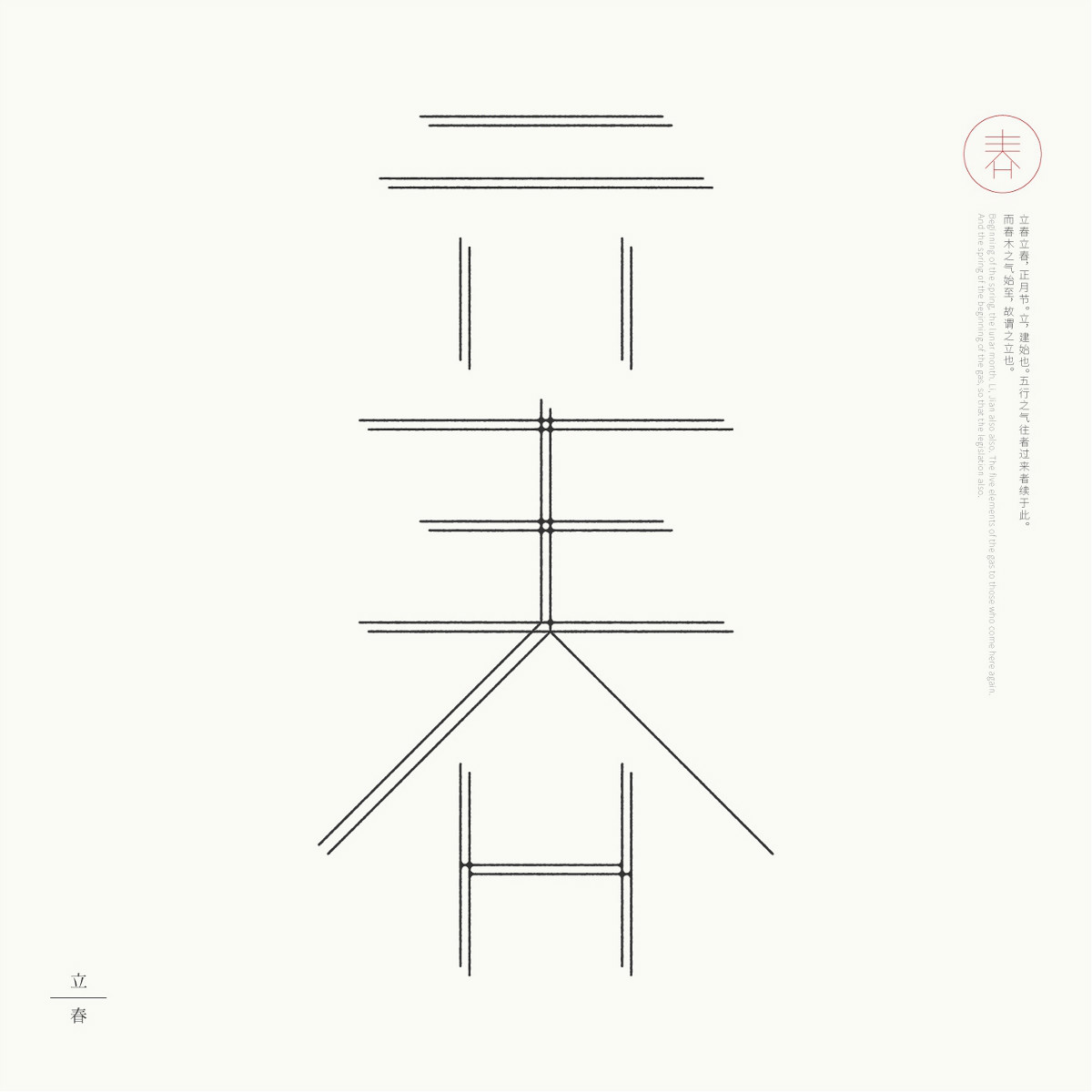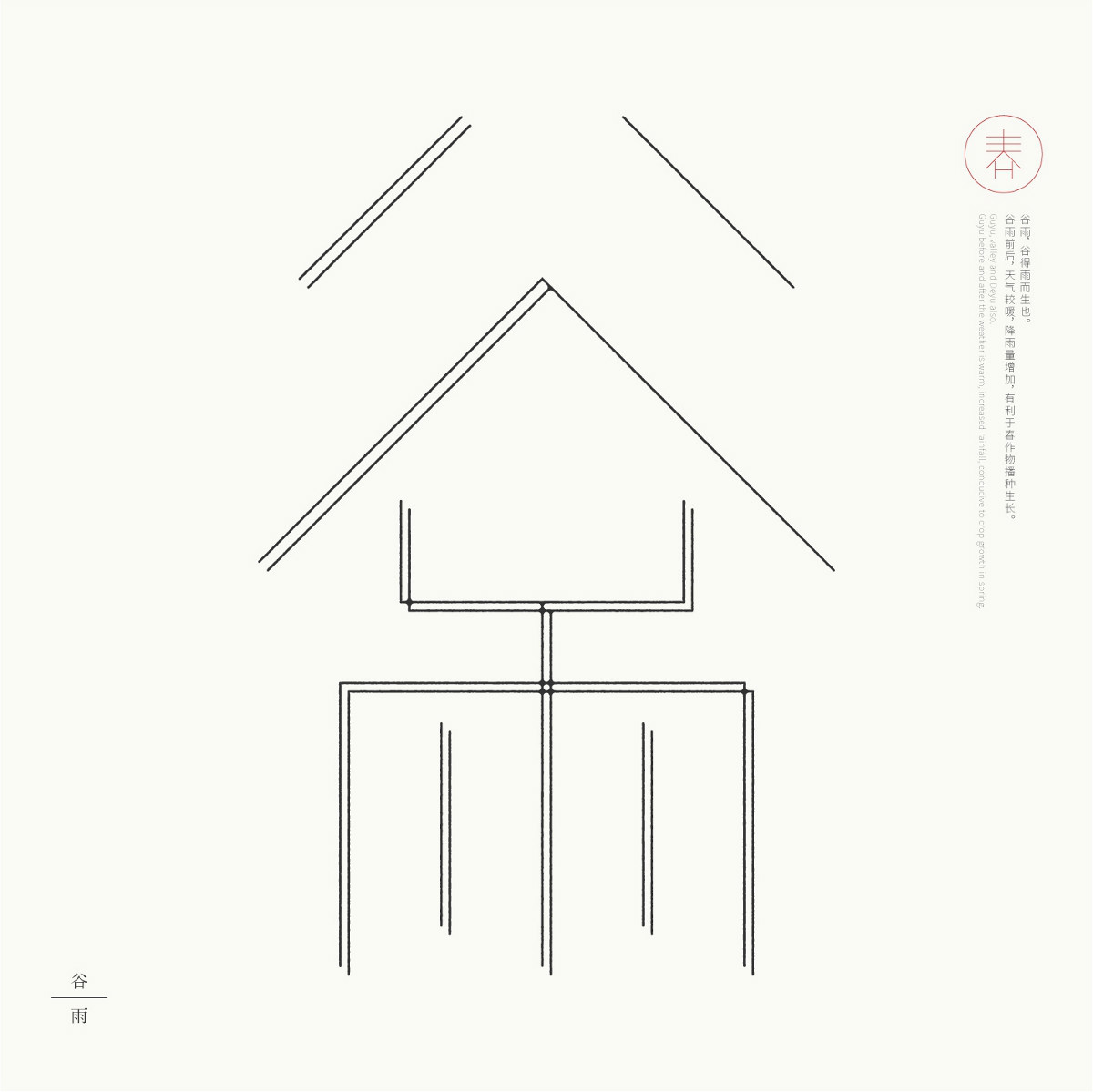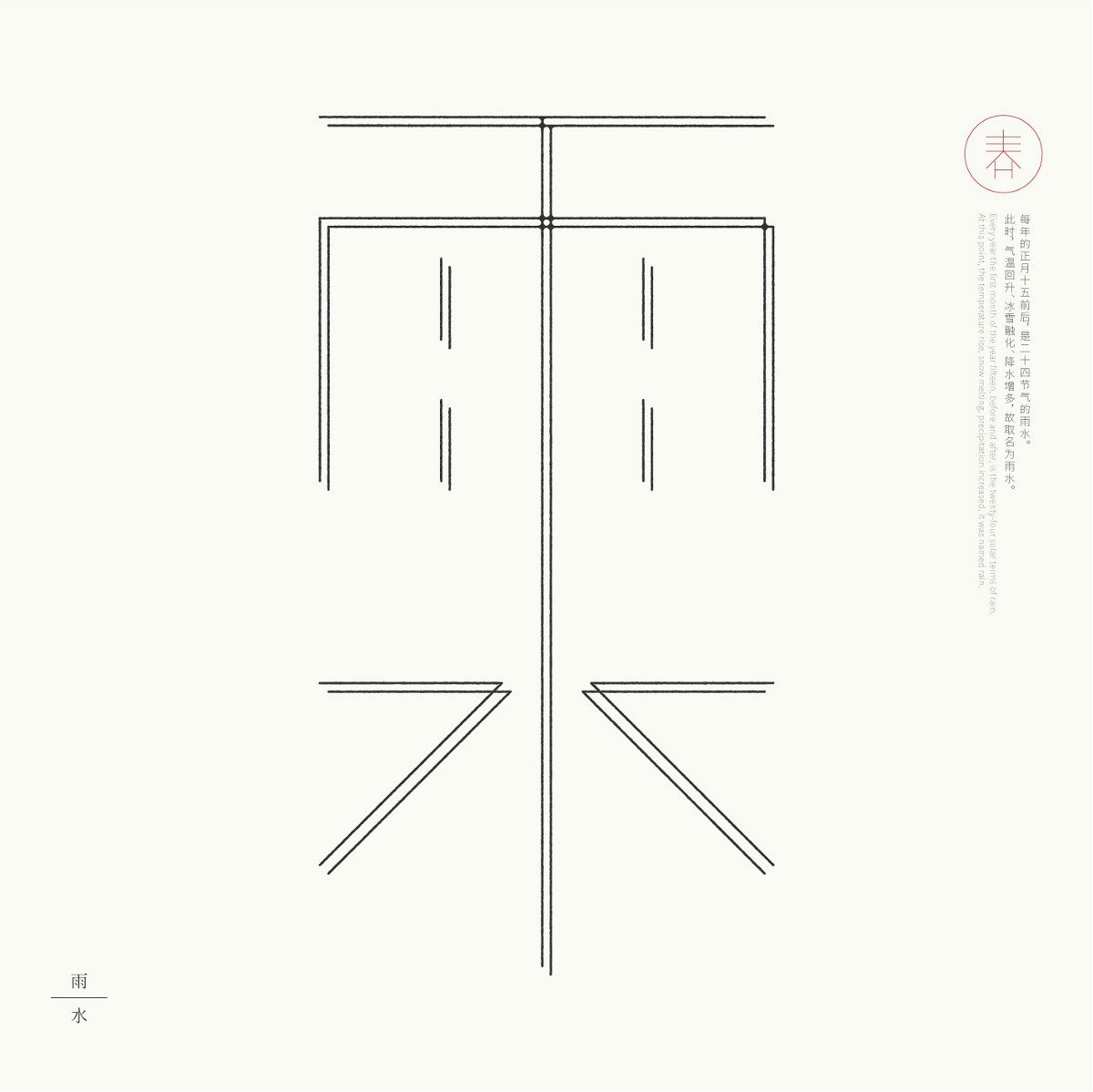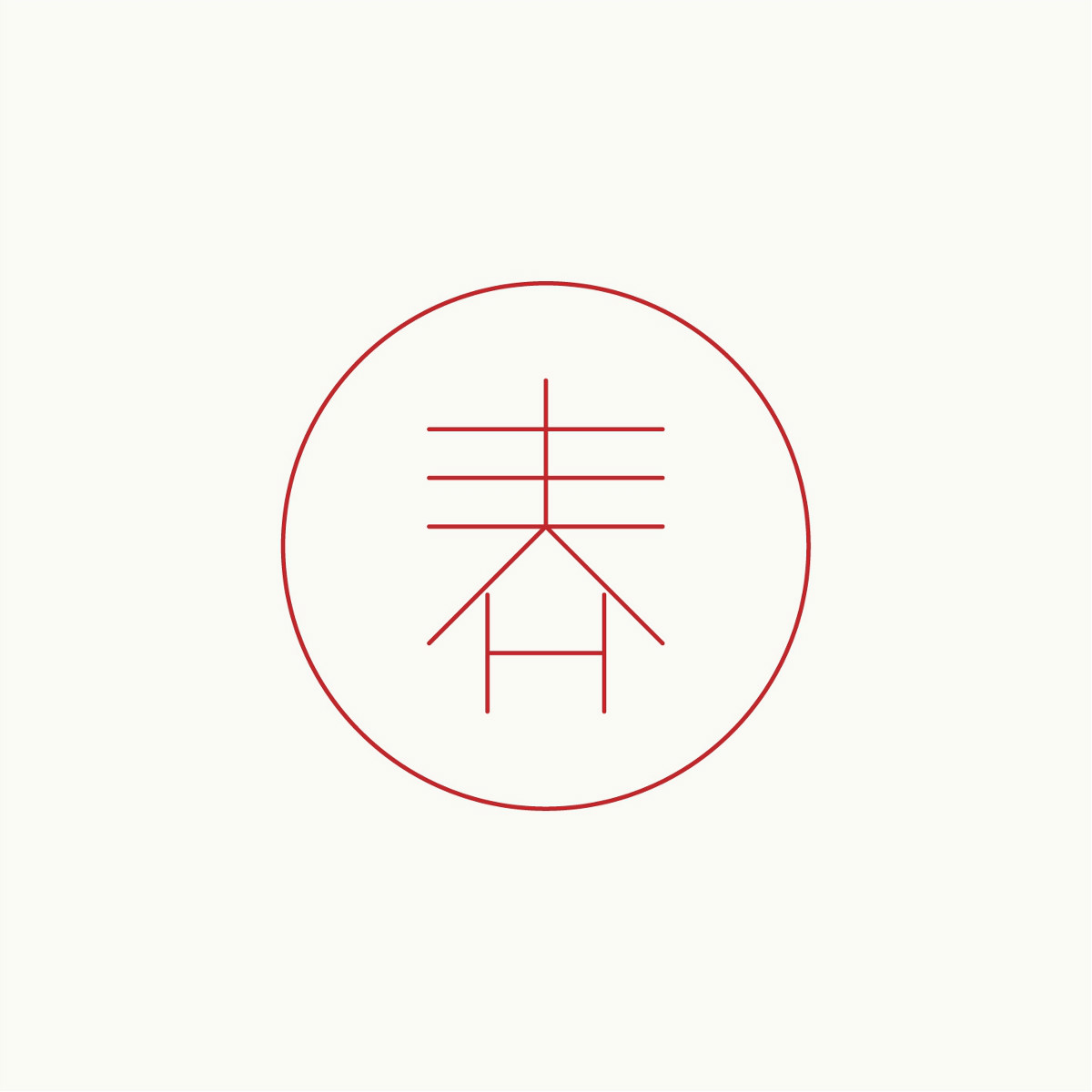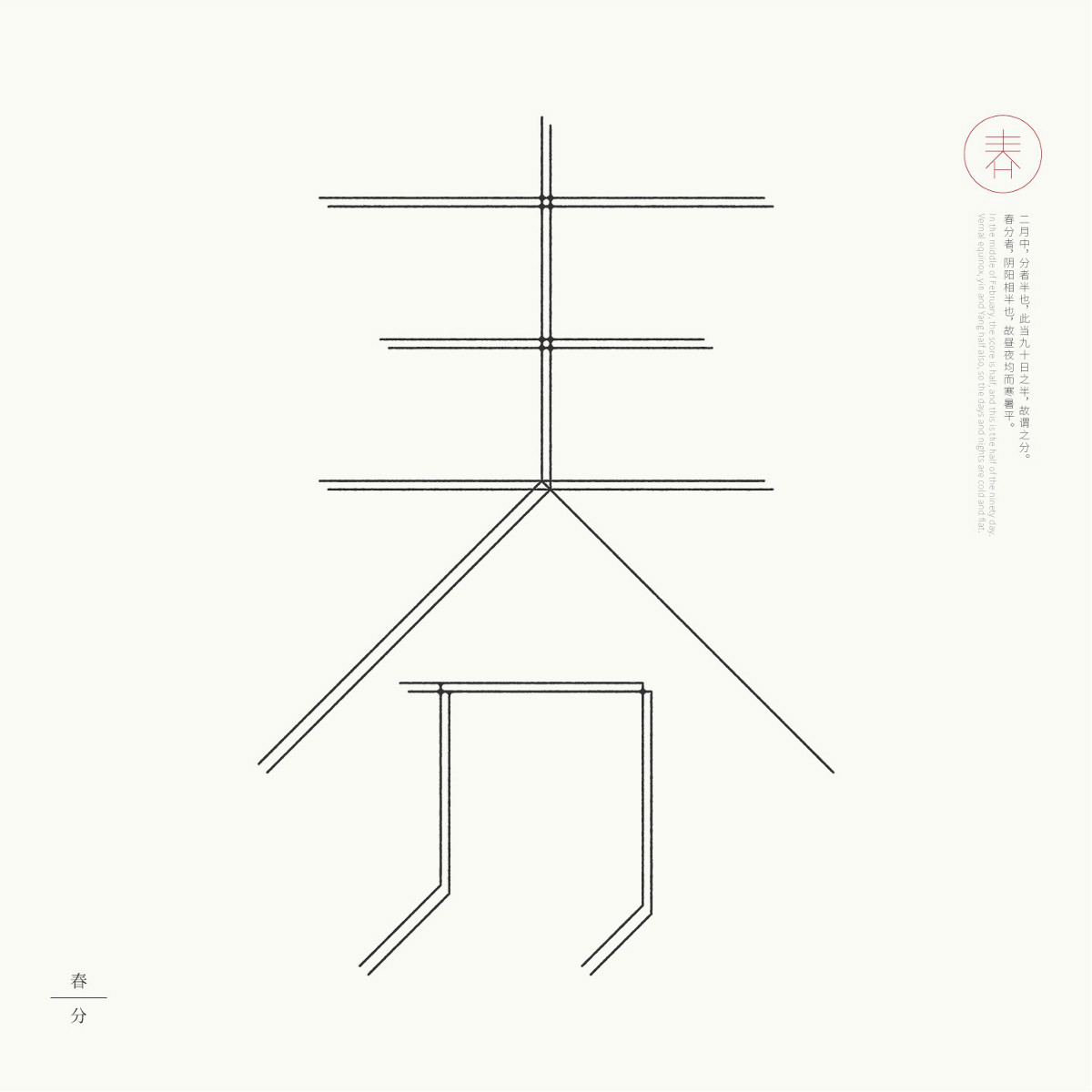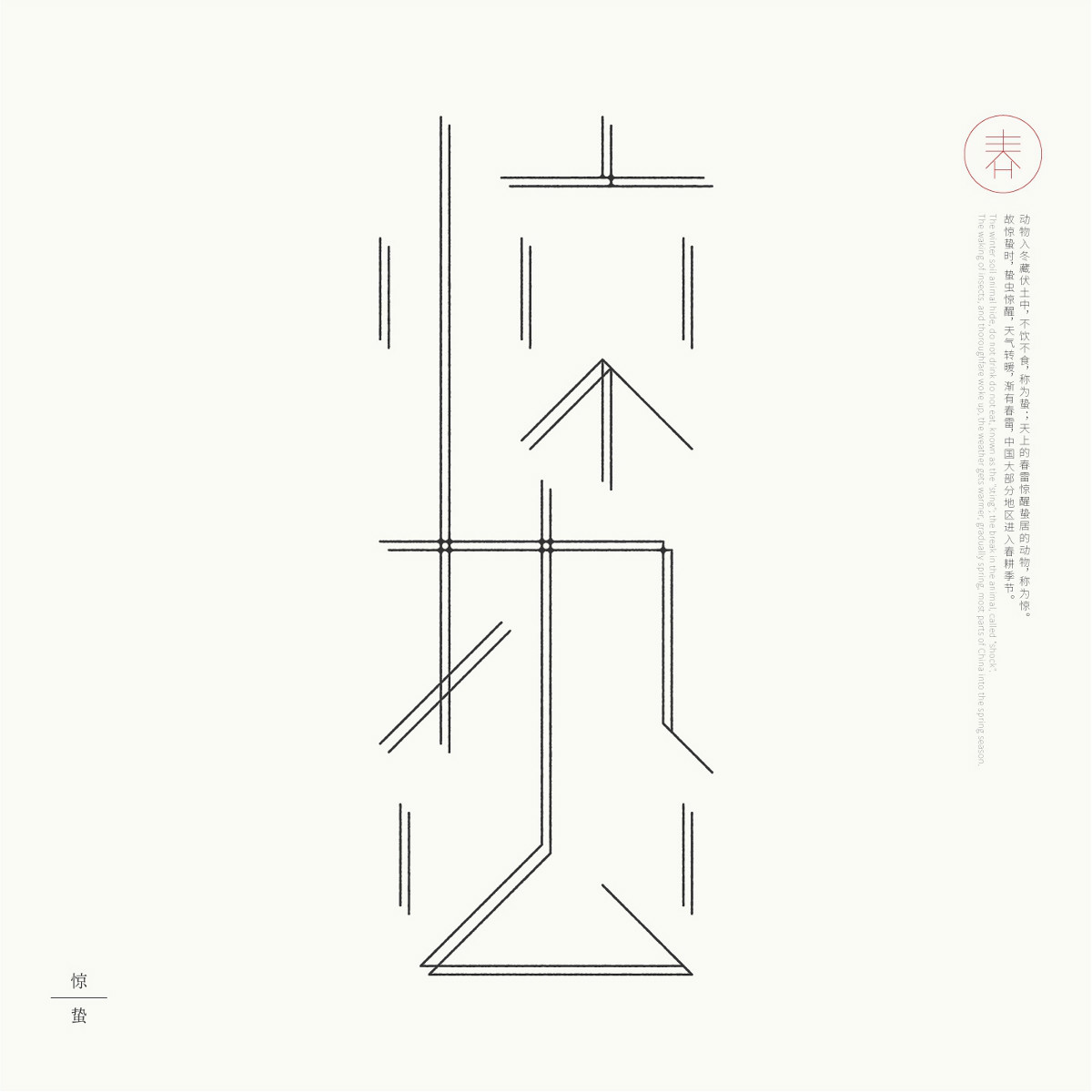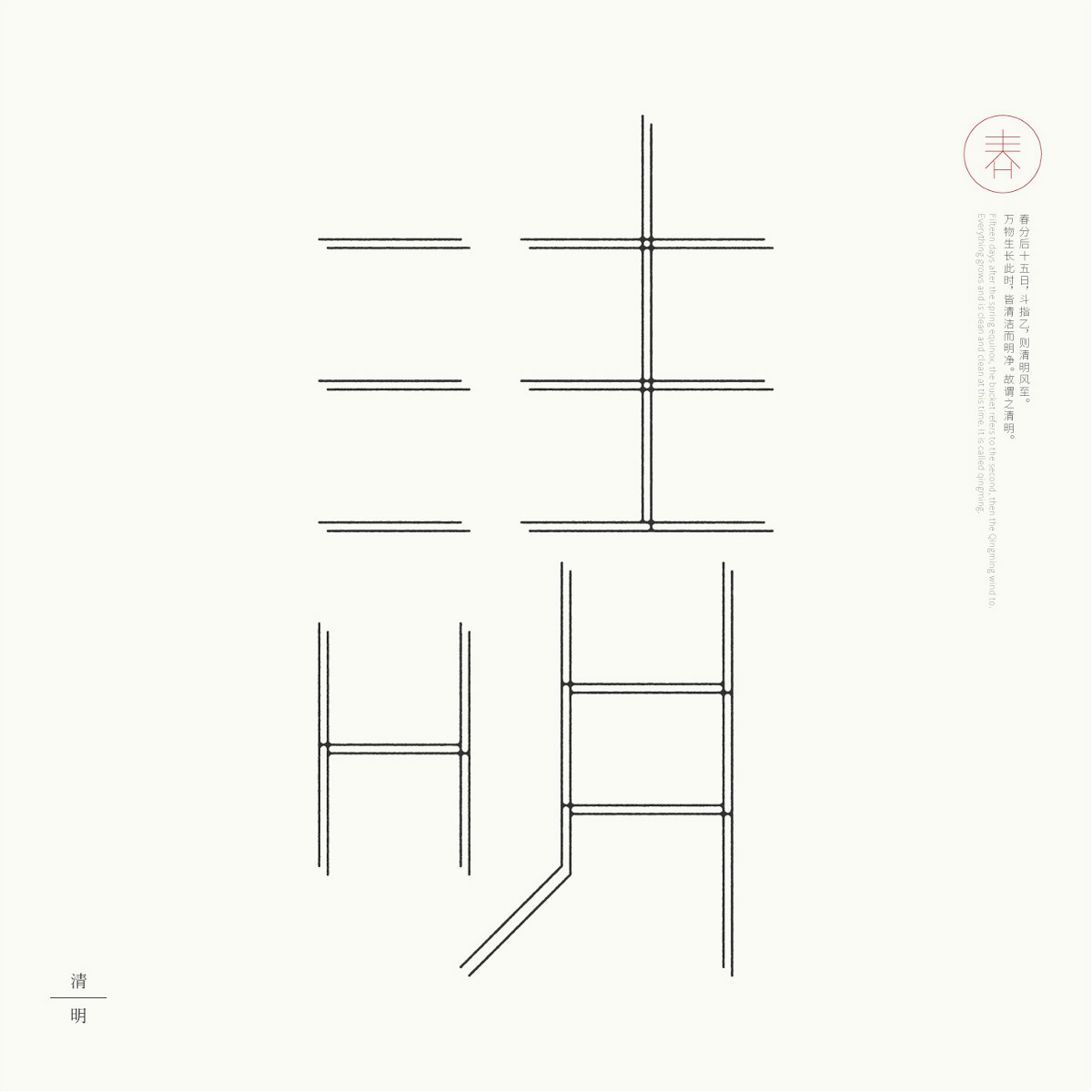
24節(jié)氣字體設(shè)計,簡約黑白藝術(shù)字體設(shè)計
春去秋來,一年四季,周而復(fù)始。這款24節(jié)氣字體設(shè)計簡潔大氣,利用黑白線條簡化字體,設(shè)計感強(qiáng)烈。下面家佳樂文學(xué)小編為你帶來24節(jié)氣字體設(shè)計,簡約黑白藝術(shù)字體設(shè)計。
24節(jié)氣字體設(shè)計,簡約黑白藝術(shù)字體設(shè)計